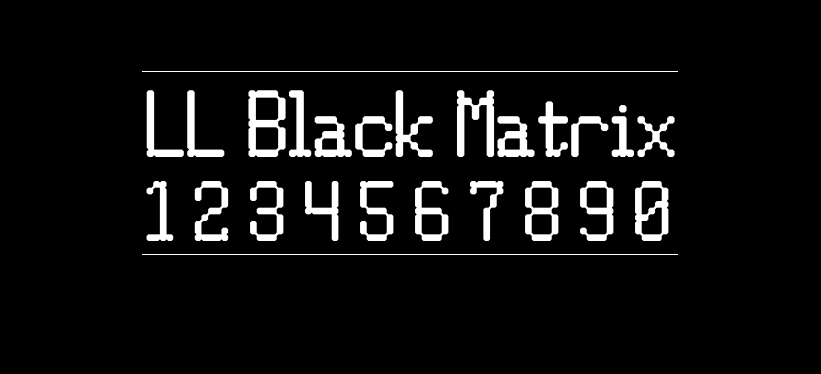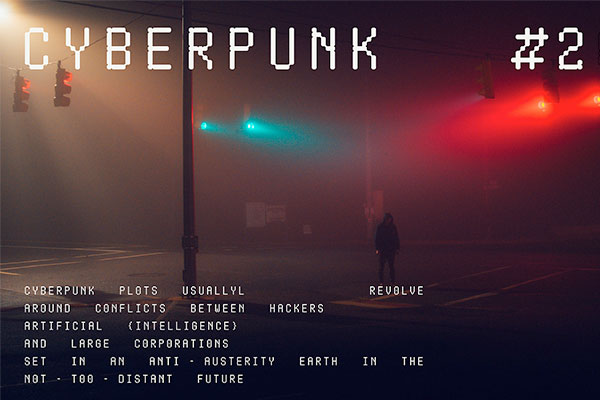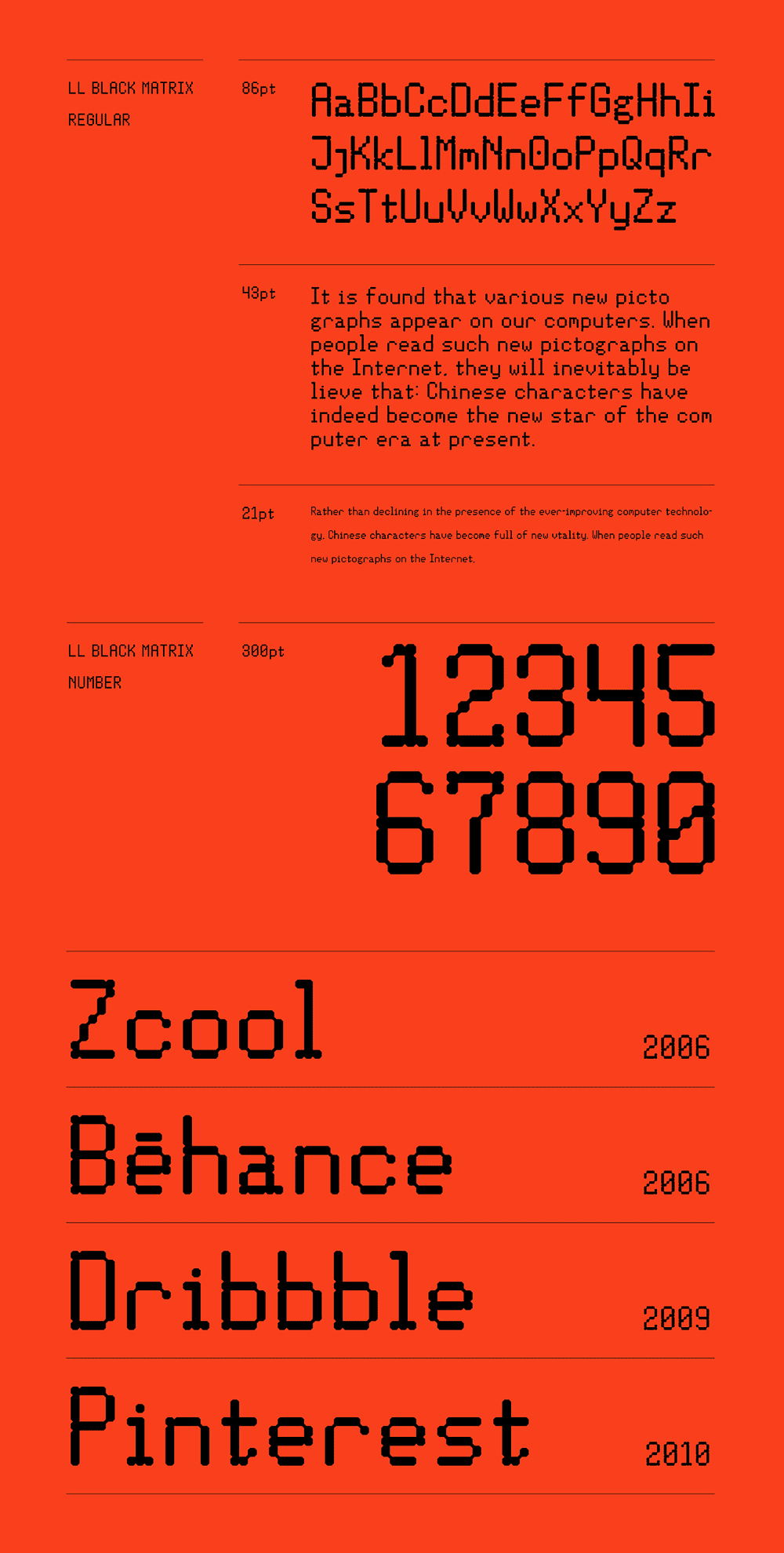
LL Black Matrix
LL Black Matrix是来自站酷的设计师LUKE_创作的一款英文字体,由针式打印机字体延伸而来的一款拉丁文字库。整体是基于5乘9的网格来规范,通过对点阵的连接让字体视觉上变的更加整体。它包含300+字符并支持100+语言。
该字体有种旧LCD屏幕游戏的像素风格,可满足多种的拉丁文使用场景。为了大家能更好的使用更酷炫的字体,作者决定开放这款字体的版权,可以用在任何媒介,包括电子屏幕、印刷品、APP等,并放心的用于商业目的。